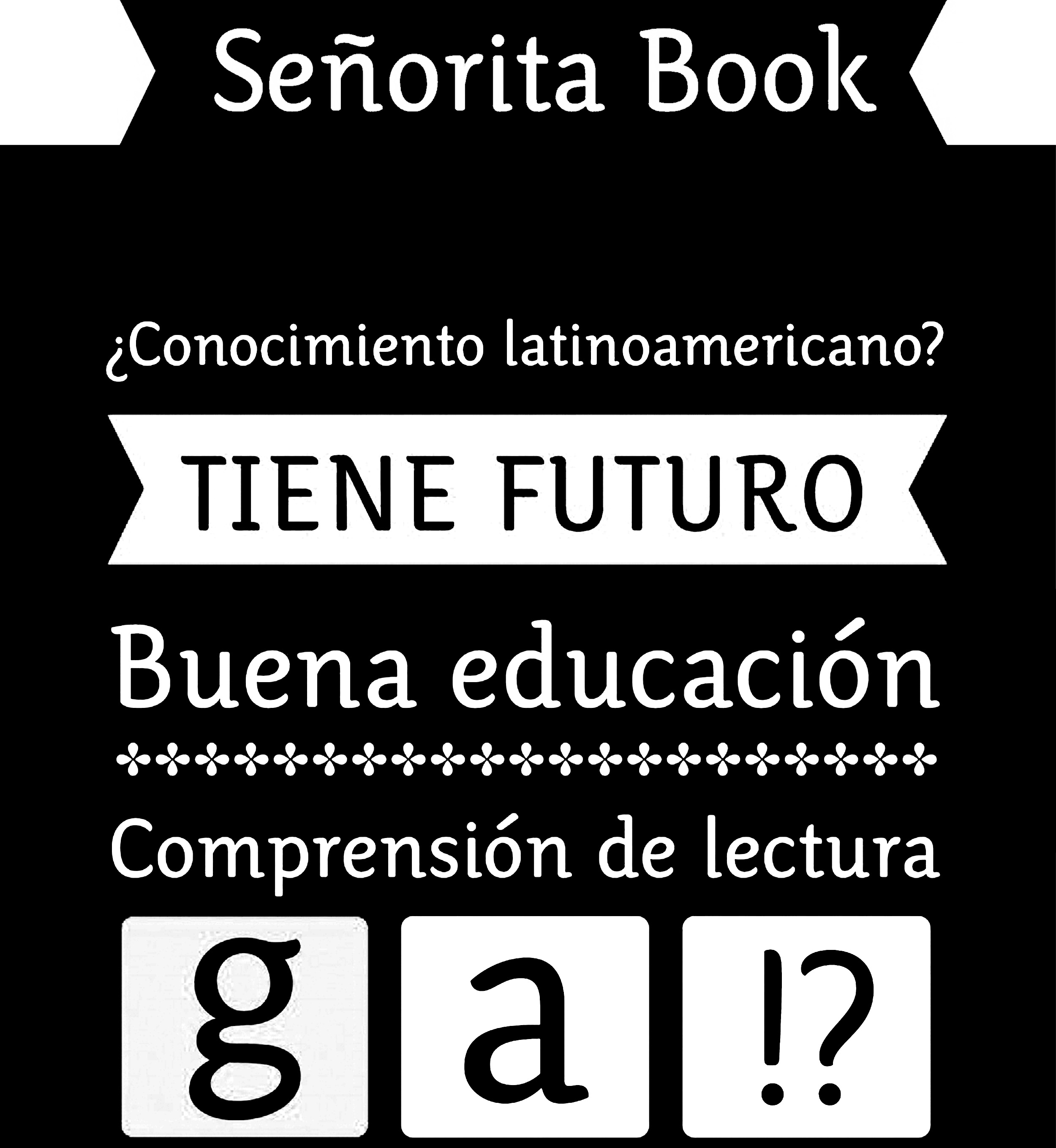
Señorita
| Año | 2007 |
| Créditos | Paula Barahona |
| Descripción | Señorita es una tipografía para textos infantiles. Su carácter amigable es acompañado de rasgos suaves y terminaciones híbridas que insinúan el gesto de escritura. Fue seleccionada para ser exhibida en la 3era Bienal de Tipografía Latinoamericana del año 2008 |
| Clasificación | Texto |
| Familia(s) | Sans serif |
| Estudio | Vicencio |
| Cliente | Proyecto académico de postítulo (Diplomado en Tipografía UC) |
| Reconocimientos | Bienal de Tipografía Latinoamericana. Tipos Latinos 2008 |